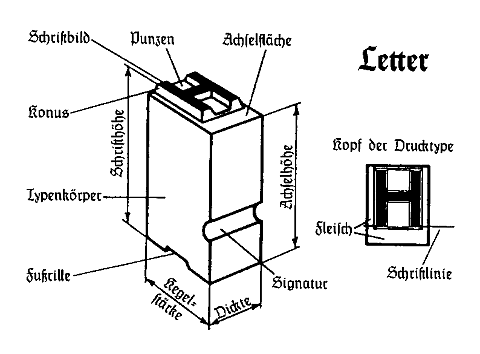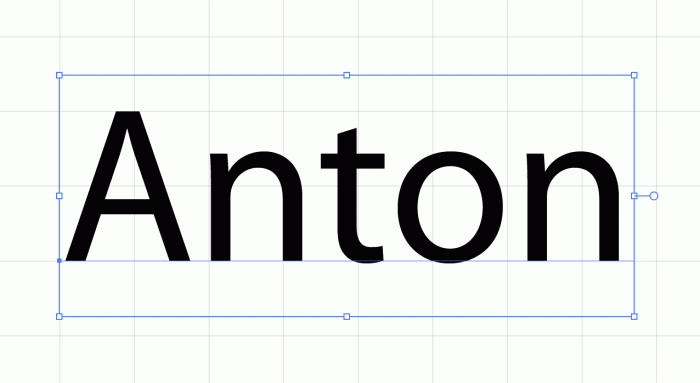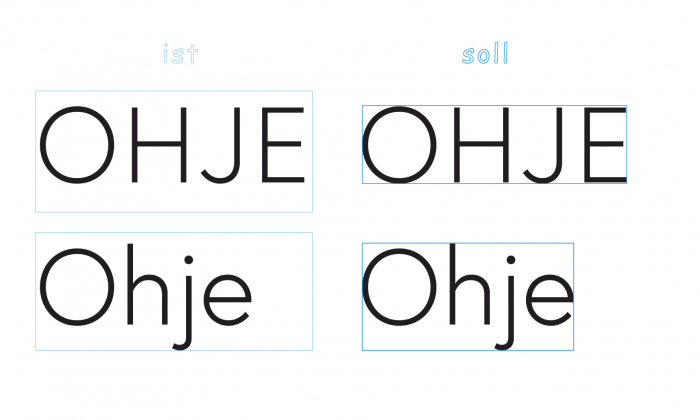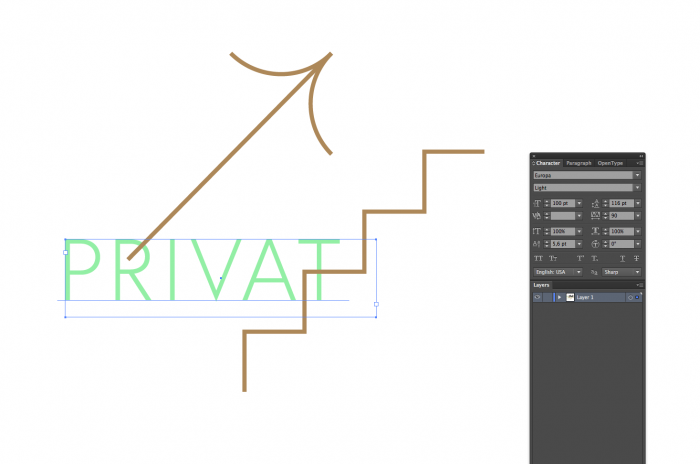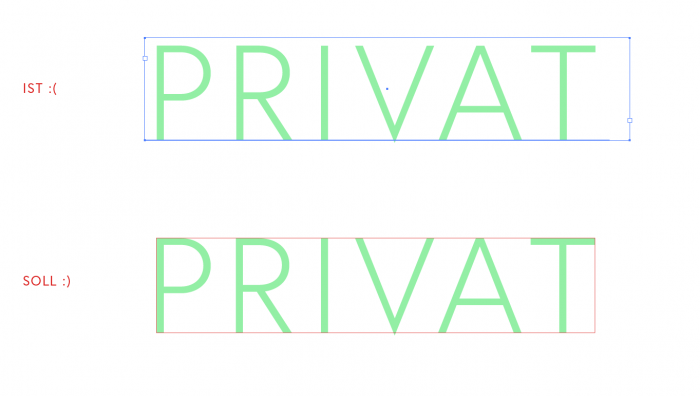
Illustrator — Textbox exakt anpassen
Gerade leicht am verzweifeln aufgrund von ungewohnt genauer Textarbeit im Illustrator die ich eigentlich nur von Indesign her gewöhnt bin, die aber aufgrund der Dimensionen sein müssen.
Wie schaffe ich es die Textbox (100pt) exakt an das abgesetzte Textstück anzupassen bzw. welche Einstellungen muss ich vornehmen um die »Pounding Box« genau entlang der Versalhöhe entlang verlaufen zu lassen? Natürlich könnt ich den Text in Pfade konvertieren und damit als Objekt weiterarbeiten, genau das möchte ich aber nicht denn der Text soll editierbar bleiben.
Ich würde gerne die Textbox so anpassen, dass sie exakt um den Text herum verläuft.
Mittlerweile habe ich die Versalhöhe und sowie die linke Linie der Textbox schon brauchbar mittels Kerning-Funtkion und Baseline-Shift eingerichtet (siehe Screenshot), einzig die untere und rechte Kante der Textbox schaffe ich nicht einzurichten da der Text immer verschwindet wenn ich die Box zu nahe an den Text ziehe.
Die Aufgabe erfordert Genauigkeit, ansonsten würde es mir reichen mich an der Oberkante zu orientieren. (Singaletikprojekt — Siebdruck an der Wand — Einrichten der Letter unter Berücksichtung schmaler Holzpaneele)
ich habe oft die gleiche Aufgabe. Ich verwende meist zwei Ebenen, eine Ebene mit dem editierbaren Rohtext und eine Ebene mit Text als Pfad. Textänderungen kann ich so schnell umsetzen. Ich weiß natürlich nicht, ob das für Dich praktikabel ist. HTH!
Ich halte es für den falschen Ansatz, die Genauigkeit der Textgröße über den Rahmen regeln zu wollen. Das ist weder nötig, noch sinnvoll. Leg ein Raster an, rechne die Schriftgröße so aus, dass die Versalhöhe das gewünschte Ergebnis liefert — fertig. Dann kannst du überall Punkttexte setzen wie du lustig bist und sie stehen quasi automatisch richtig — völlig unabhängig von der Rahmengröße.
Das ist natürlich eine Möglichkeit.
Das ganze Dokument aber auf einem Raster basierend auf einer zweistelligen Kommazahl aus der errechneten bzw. von der Pfadform gemessenen Versalhöhe aufzusetzen ist halt dann leider nicht ganz zweckmässig. Mir ginge es eher darum die Textbox einfach per Koordinaten auf beispielsweise einer Hilfslinie anzuhängen und sie steht dann eben nicht mit der Oberkante des Rahmens an dieser sondern eben genau mit der Versalhöhe, unabhängig von Raster und dergleichen. Aber da ist vermutlich das Modifizieren des Textfeldes mittels Baseline-Shift die naheliegendste Möglichkeit …
"Oberkante des Rahmens an der Versalhöhe" setzt aber voraus, dass alle Versalien gleich hoch sind. Ein O oder J wirft dir das Konzept je nach Schriftart schon wieder über den Haufen (abgesehen davon, dass das in AI leider nicht so möglich ist, wie du dir das wünschst).
Hast du mal versucht, das über Flächen- oder Pfadtext zu lösen?
Ich glaube, um das Problem, warum sich die Textbox nicht an die Außenkonturen der Buchstaben anpassen will, zu begreifen, wäre es gut, wenigstens einmal eine alte Bleiletter in Händen zu halten.
Wie man an dieser Abbildung, besonders dem Blick von Oben auf die Letter siht, is der eigentliche Buchstabe, der auf dem so genannten Kegel sitzt rundum von mehr oder weniger breitem Platz, Fleisch genannt umgeben, sosass die Buchstaben, setzt man seinen Text Kompress, also ohne zusätzlichen Abstand (Durchschuss) die Buchstaben trozdem nicht zusammenstoßen.
Dies hat aber der digitale Font prakisch übernommen, das bedeutet, für die Anwendung sind nicht die Buchstaben.Konturen, sondern der virtuelle Kegel das Maß der Glyphen, um die diese dann die "Bounding Box" legt.
Liebe/r catfonts,
Danke für den Exkurs.
Meine Frage bezieht sich darauf, die scheinbare Zweckmässigkeit des »virtuelle Kegels« aus dem Bleisatz hinsichtlicher der Anforderung komplexer Beschriftungssysteme wo ich gerne mit der puren, editierbaren Form, abseits von Hilfs- und Rasterlinien arbeiten würde.
Genauer gefragt: kann man das Fleisch mittels einfachem, metrischen Automatismus über Illustrator deaktivieren wenn es nicht gebraucht wird oder ist Illustrator da fix an die Einstellungen gebunden welche für die jeweilige Type definiert wurde.
Die fleischgewordene Osternachricht von Adobe lautet jedenfalls nüchtern:
Genauer gefragt: kann man das Fleisch mittels einfachem, metrischen Automatismus über Illustrator deaktivieren wenn es nicht gebraucht wird oder ist Illustrator da fix an die Einstellungen gebunden welche für die jeweilige Type definiert wurde.
Die Type definiert da gar nix. Die Schrift wird im Rahmen verankert (Grundlinie, Kegel-Oberkante etc.) und der Rahmen kann mit oder ohne Schriftänderung skaliert werden. Und genau deshalb sage ich ja: lass diesen Zwischenschritt weg, über den Rahmen indirekt die richtige Schriftgröße erreichen zu wollen. Der Rahmen weiß nicht, was sich in ihm abspielt und ist daher auch kein geeigneter Hebel, um die in ihm befindliche Schrift genau einzustellen.
Die von dir genannten Feinheiten schreit nach flexiblen Optionsmöglichkeiten: »Textblock skalieren an Versalhöhe«, »Texblock skalieren an maximaler Höhe«. Da es sich bei mir bisweilen um Einzelfälle handelt die sich nicht aneinander ausrichten, wäre das durchaus denkbar. Wie man sieht ist das sozusagen temporäre oder permanente ausschalten der »Kegelhöhen- und breiten« scheinbar weiterhin Science Fiction, über die Zweckmässigkeit zu diskutieren lohnt sich meines Erachtens aber schon ...